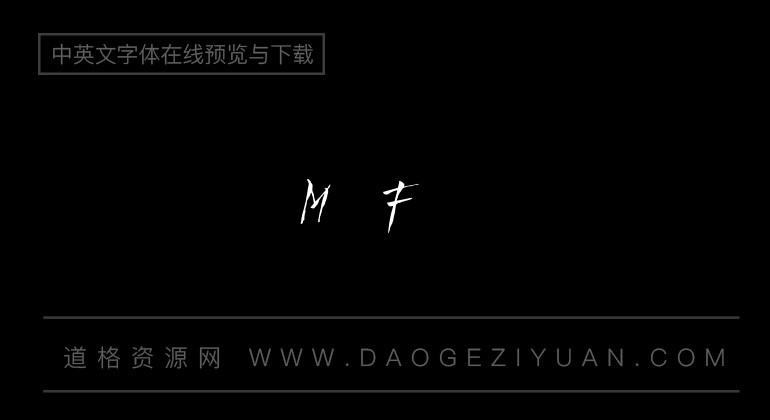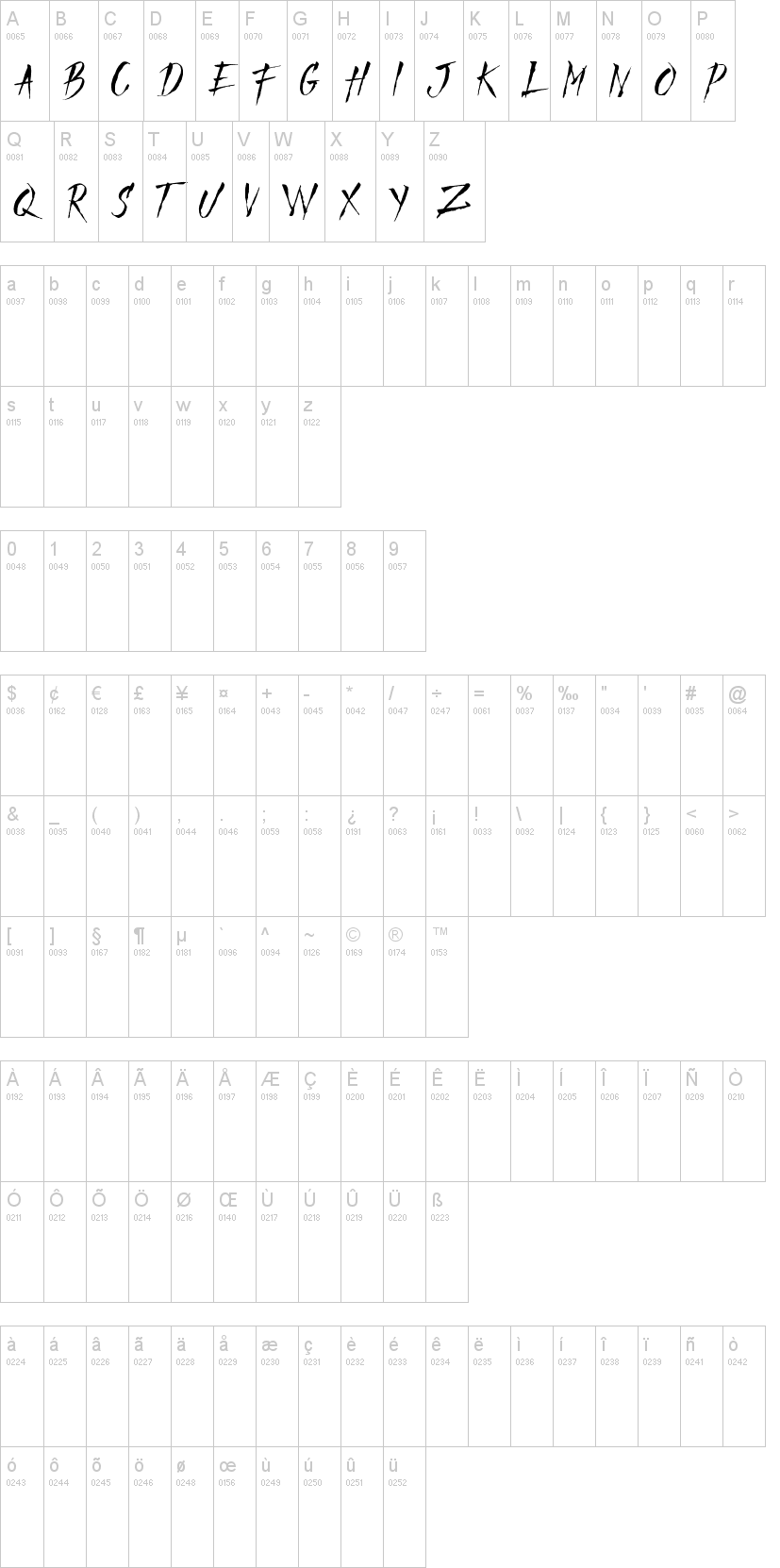
Mad Faith是一种时尚的手写风格字体,由设计师Hendra Pratama于2019年创建。该字体特点是字母之间的连通式设计,使得整个字体看起来像是由一个笔画写成的,同时也带有一些涂抹的感觉。 Mad Faith字体的设计风格非常适合用于设计时尚、艺术性强的品牌标志、海报、宣传品等。该字体支持多种语言,并包含了标准的字母、数字、标点符号等基础字符,同时还包含了一些装饰性的字符,例如下划线、星号等,可以很好地补充和丰富设计元素。 总的来说,Mad Faith字体是一种很有个性和艺术感的字体,适合用于许多创意设计项目中。内容介绍
Mad Faith是一款非常不错的手写艺术字体,具有很好的视觉感,适合于文化类的宣传设计、商业类品牌的广告和产品包装设计以及个性化文字排版等较多场景。